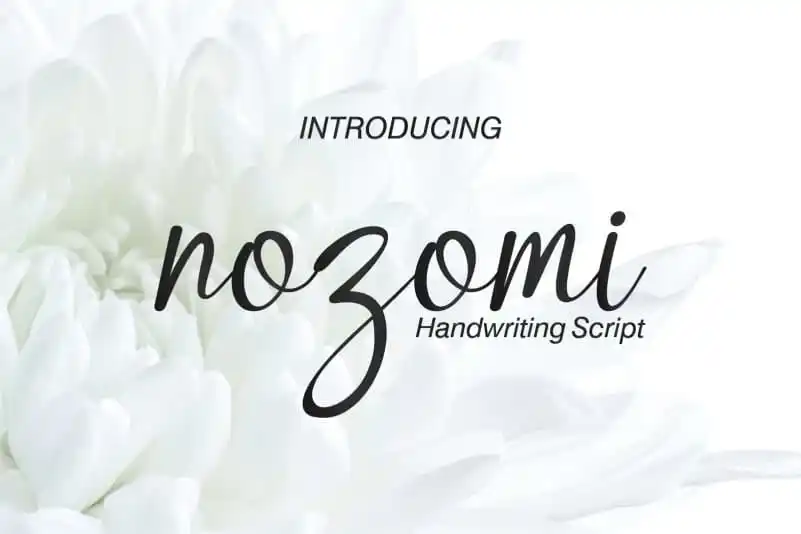
Nozomi Handwriting Script Font – Fonte Grátis
Nozomi Handwriting Script Font
A Nozomi Handwriting Script Font é uma elegante caligrafia cursiva para designers e criativos de todo o Brasil. Seja você quem busque inspiração para seu feed do Instagram ou esteja trabalhando em projetos DIY, esta fonte vai transformar suas ideias mais pessoais e autênticas em verdadeiros itens de arte. Com uma personalidade descontraída e agradável, ela é perfeita tanto para uma postagem leve no Instagram quanto para um trabalho de caligrafia DIY com significado ímpar. Jprint Studio criou esta fonte pensando em todos vocês que querem expressar-se de forma única e divertida através do design visual, tornando qualquer projeto autêntico e encantador.
Designer: Jprint Studio